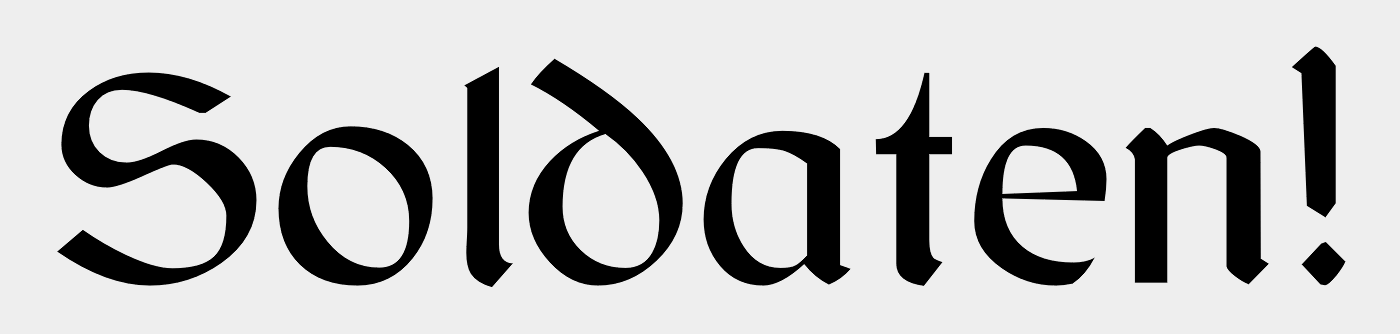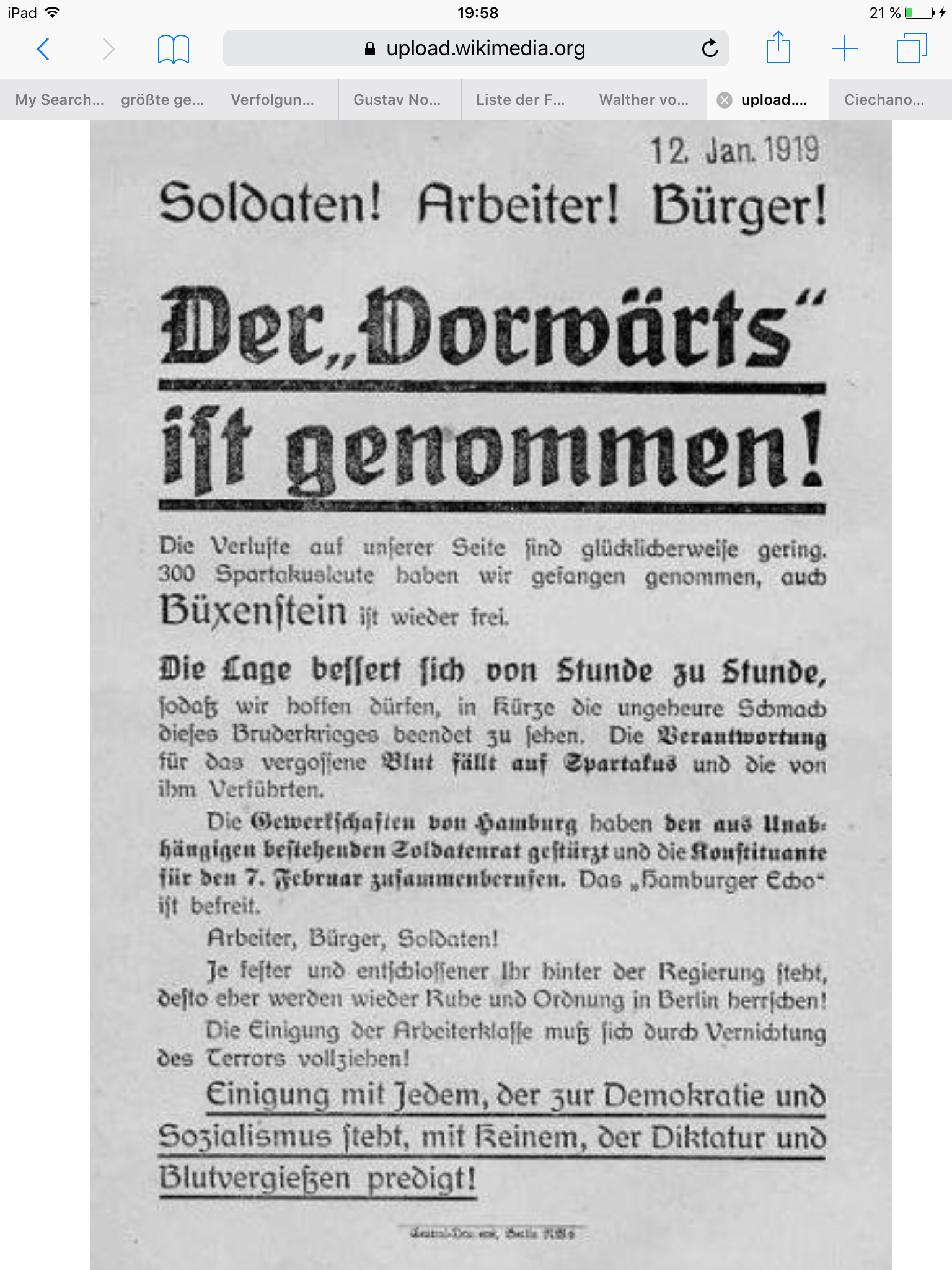
Schrift des „Vorwärts“ von 1919
ich suche die von der Zeitschrift „Vorwärts“ im Jahr 1919 verwendete Schrift (siehe Bild). Ich nehme an, dass es eine Art Rundgotisch ist?
Das hätte ich genauer spezifizieren solle. Ich suche die Schrift des nicht ausgezeichneten Fließtextes.
PS: Ich finde das interessant, dass Fraktur als Auszeichnung genutzt wird.